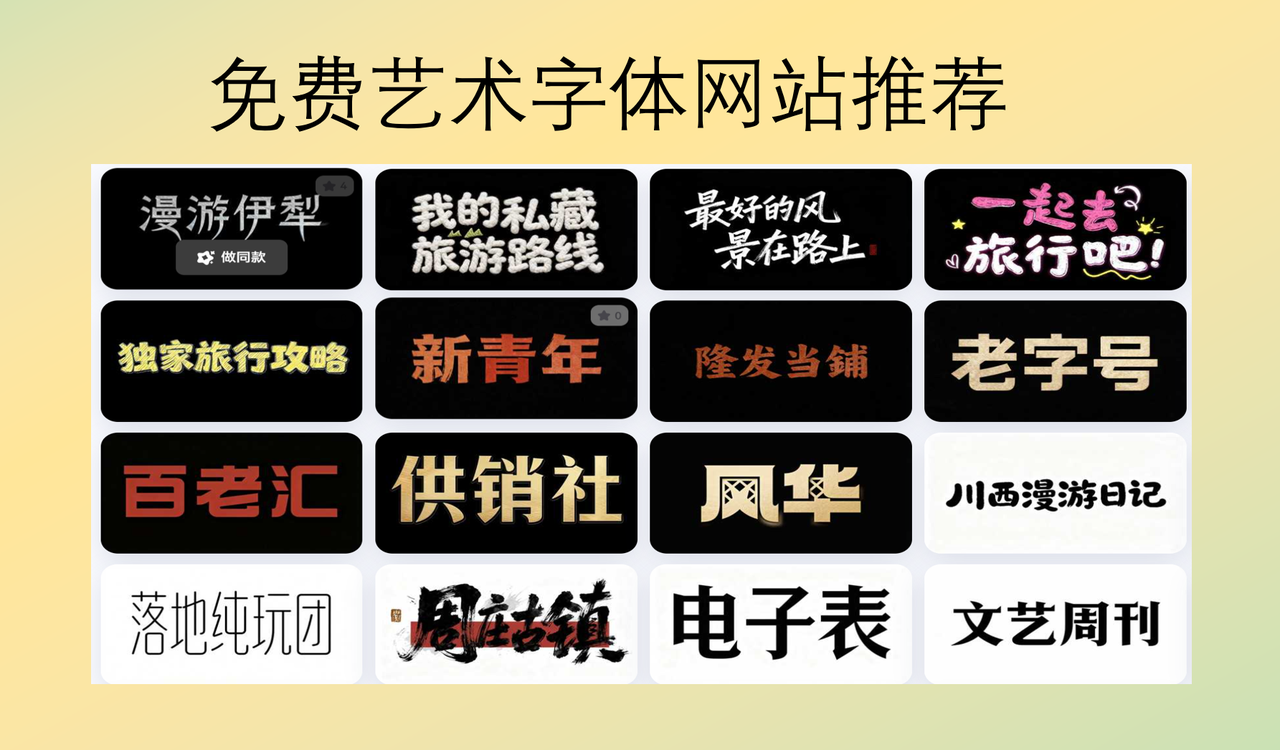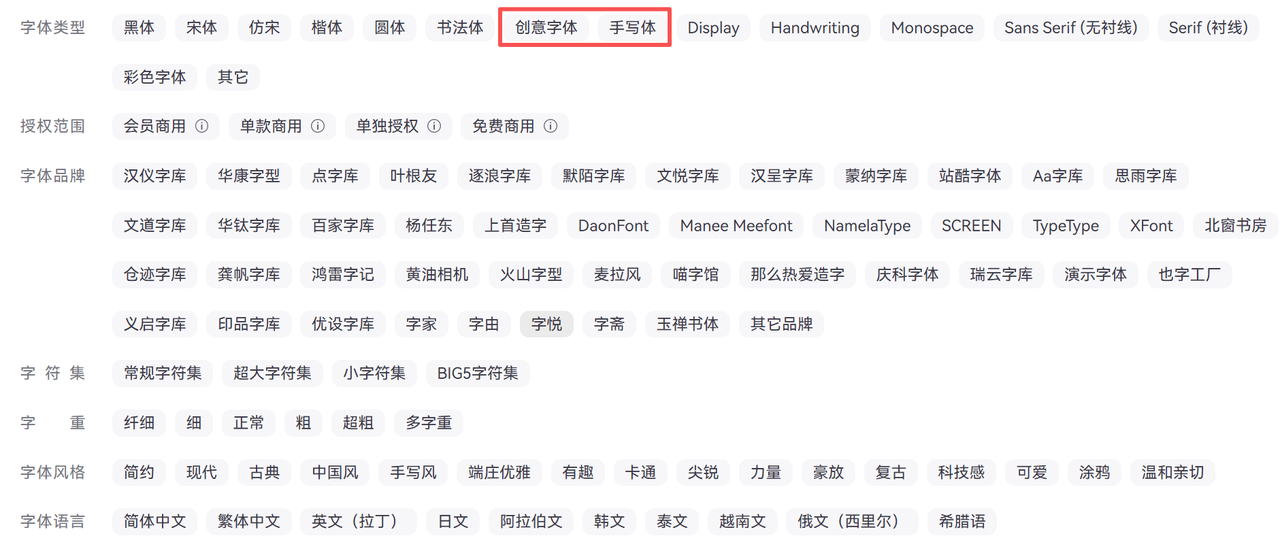
免费艺术字体网站推荐:8个可商用字体平台分享
系统自带的宋体、黑体太普通,想要的艺术字体要么收费,要么下载后发现商用有风险。
我整理了一批真正免费、可商用的艺术字体网站。这些网站不仅字体质量高,而且版权清晰,用上它们之后,我做图效率提升了一半,再也不用担心版权问题。下面分享8个免费艺术字体网站分享给你。
字由拥有非常多的艺术字体资源,并且你不用一个个的下载和安装字体,使用字由客户端就能够快速的激活、使用和管理字体。
筛选分类获取艺术字体
字由通过非常清晰的字体分类,如果想要获取艺术字体,你可以筛选字体类似为“创意字体”、“手写体”,也可以在字体风格中选择“手写风”、“中国风”等艺术分类。
字由除了提供丰富的艺术字体之外,字由 AI 字体还能一键生成艺术字体
打开 AI 生成字体功能页面,根据自己的需求搜索艺术字体类型,比如搜索“霓虹”
进一步筛选自己想要的艺术字体模板,替换为自己的文字,就能一键生成同款艺术字体了。
100font.com
我经常在这里找一些小众但很有个性的字体。上次做咖啡店菜单,用的是"悠哉字体",手写感很强,客户说比之前那版有温度多了。
网站的好处是分类清晰,有"黑体""宋体""手写体""像素体"等标签,还能按字重筛选。每个字体都附上了授权说明文件,下载前能看清楚使用范围。
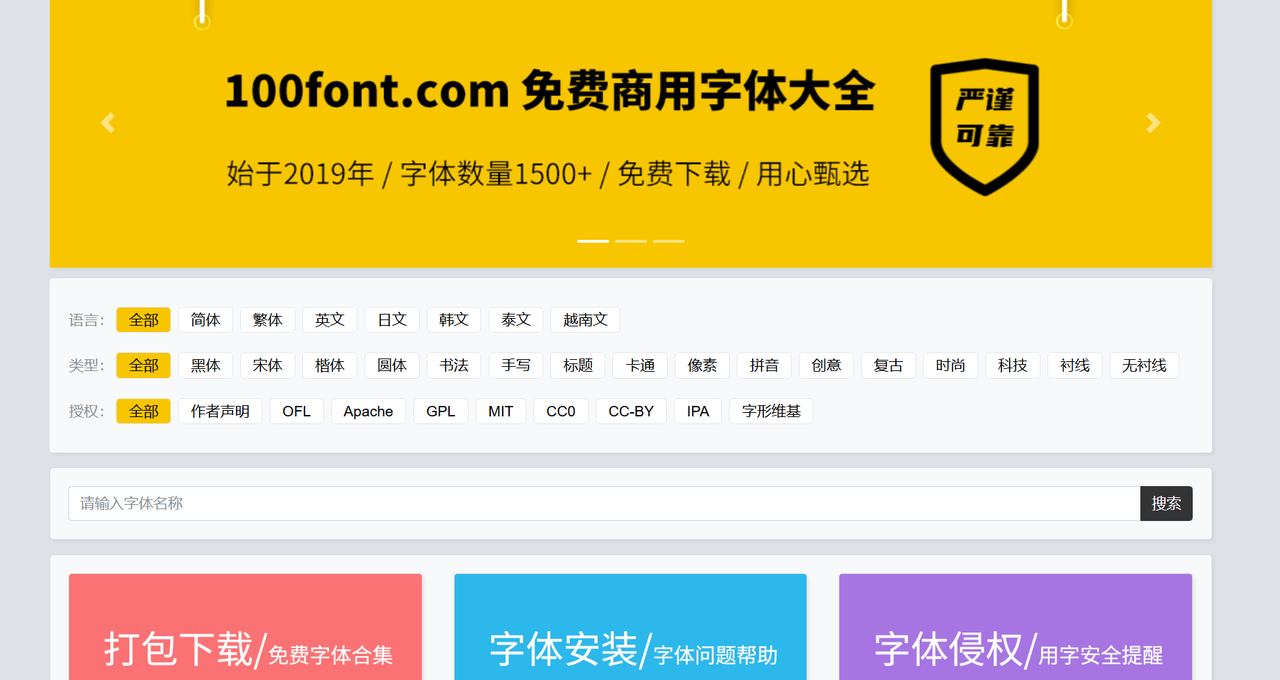
猫啃网
猫啃网是字体爱好者维护的网站,更新很勤快。它最大的特点是会把字体的授权协议翻译成大白话。比如有些字体"个人免费,商用需授权",它会明确写出来,不用你自己去研究繁琐的授权文档。
我在这里发现了"小赖字体"和"沐瑶软笔手写体",都是个人设计师免费开放的,用在手账排版和文艺类海报上效果特别好。
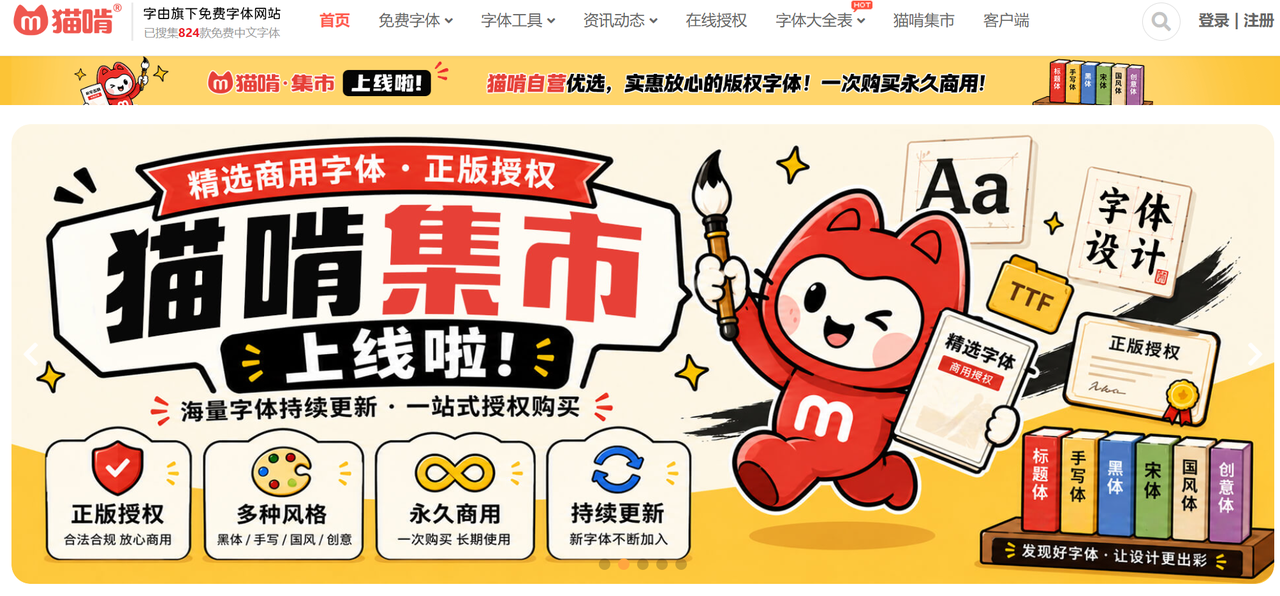
字体天下
老牌字体下载站,资源非常全。虽然里面有付费字体,但免费区的字体也不少。我一般会在搜索时加上"免费"关键词,然后仔细看下载页面的授权说明。
这个网站适合用来找特定风格的字体,比如"广告""海报"等主题字体,它的标签做得比较细。
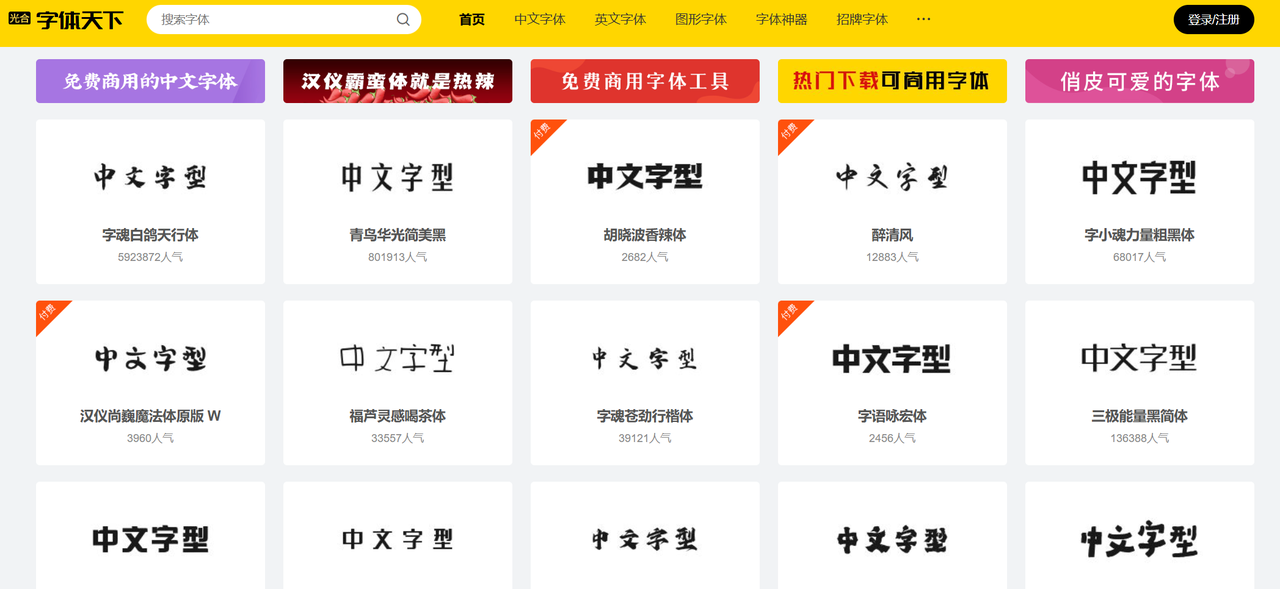
求字体网
这是一个识别字体的网站,但也提供字体下载。我用它最多的场景是:看到别人的设计作品,不知道用的什么字体,就截图上传到求字体网,它会识别出来并提供类似字体的下载链接。
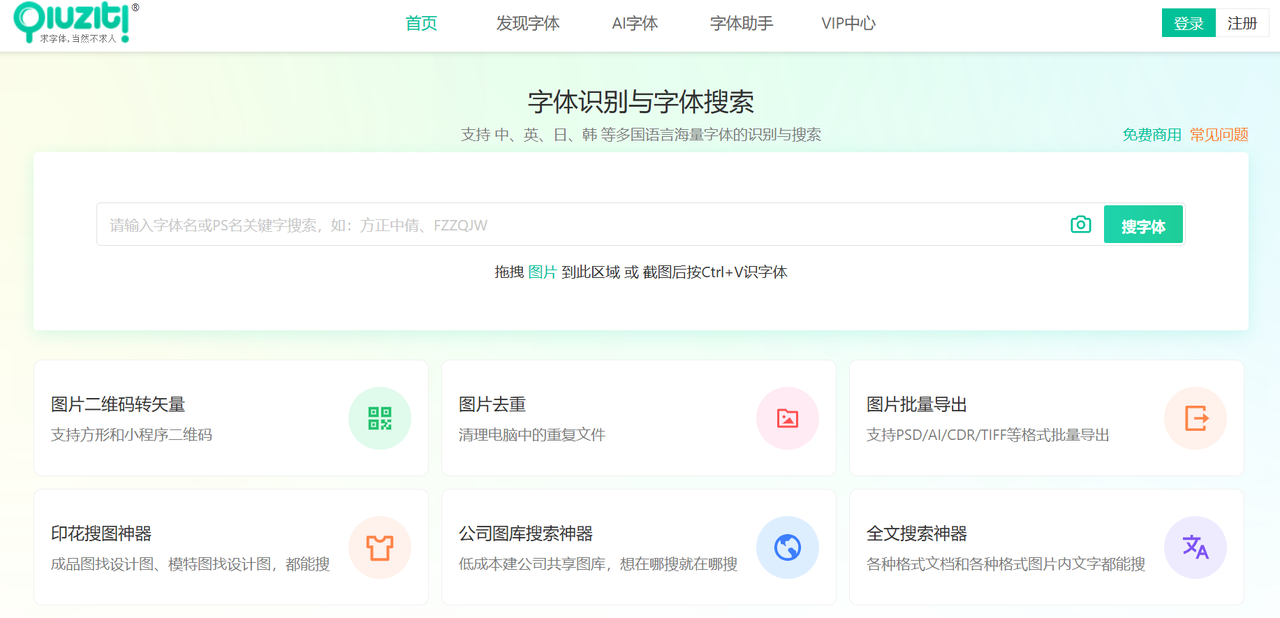
站酷字库
站酷是设计师聚集的平台,他们推出了好几款免费商用字体。"站酷高端黑""站酷快乐体""站酷文艺体"都是我常用的。高端黑适合做科技类海报,快乐体适合活动宣传,文艺体适合书籍封面。这些字体的好处是设计感强,但又不会太夸张,日常工作场景都能hold住。
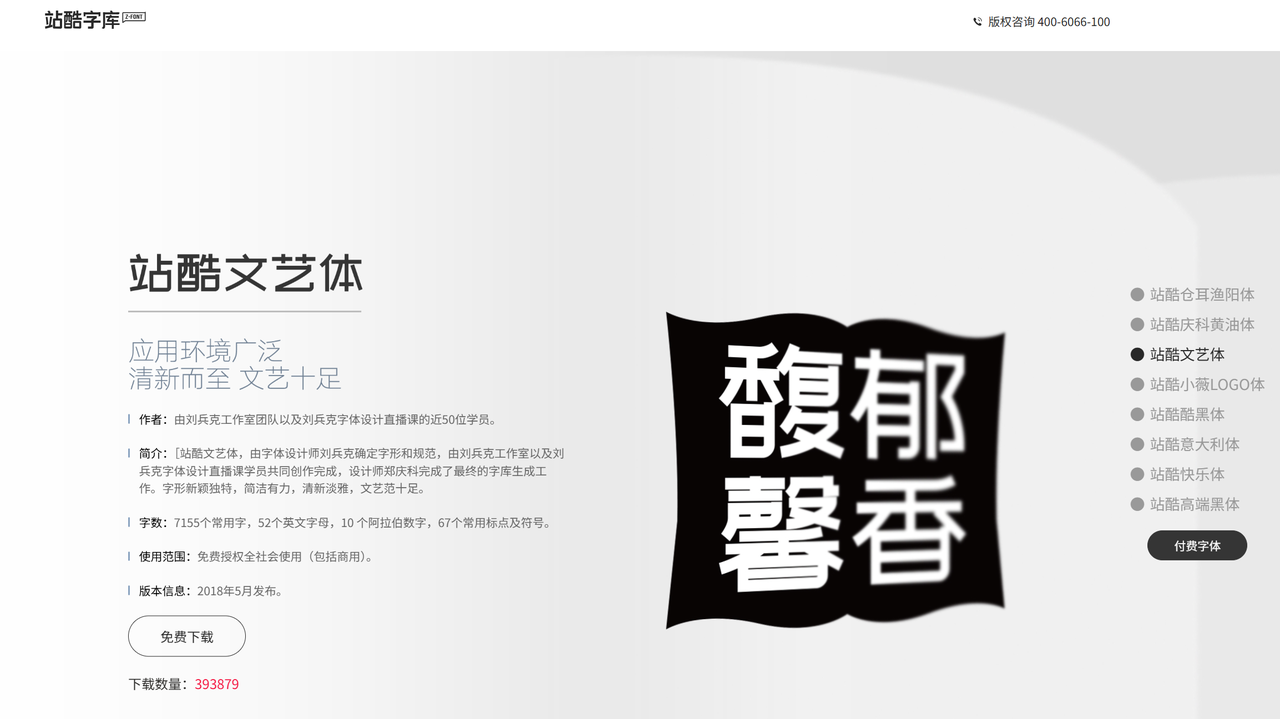
fontsquirrel
英文字体资源库,全部免费商用。我做英文LOGO或者海报标题时会来这里找字体。它有个"Font Identifier"功能,可以通过上传图片识别英文字体,准确率挺高。
推荐它家的手写体和复古字体,比如"Pacifico"和"Bebas Neue",我用在咖啡店和服装店的宣传物料上,客户反馈都不错。
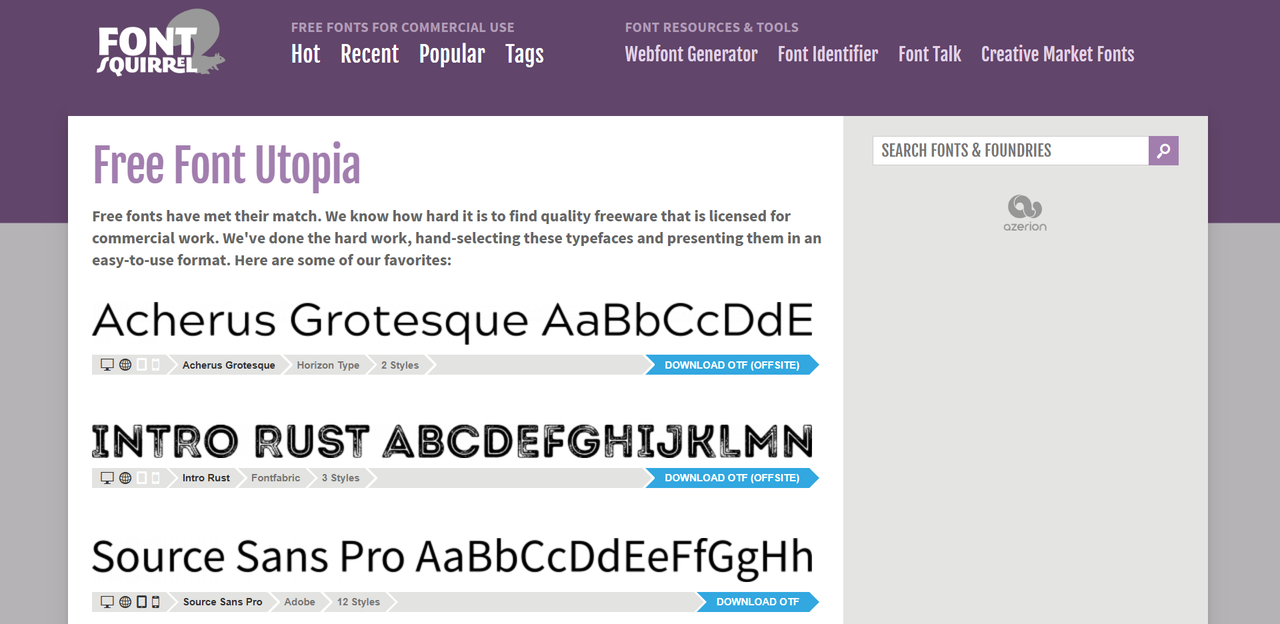
自由字体
这是一个字体导航站,把各种免费字体网站都整合在一起。我一般在找不到合适字体时,会打开这个网站搜索。同时它按风格分类,有"艺术""手写""促销"等分类,省去了一个个网站翻的时间,适合赶急活的时候用。
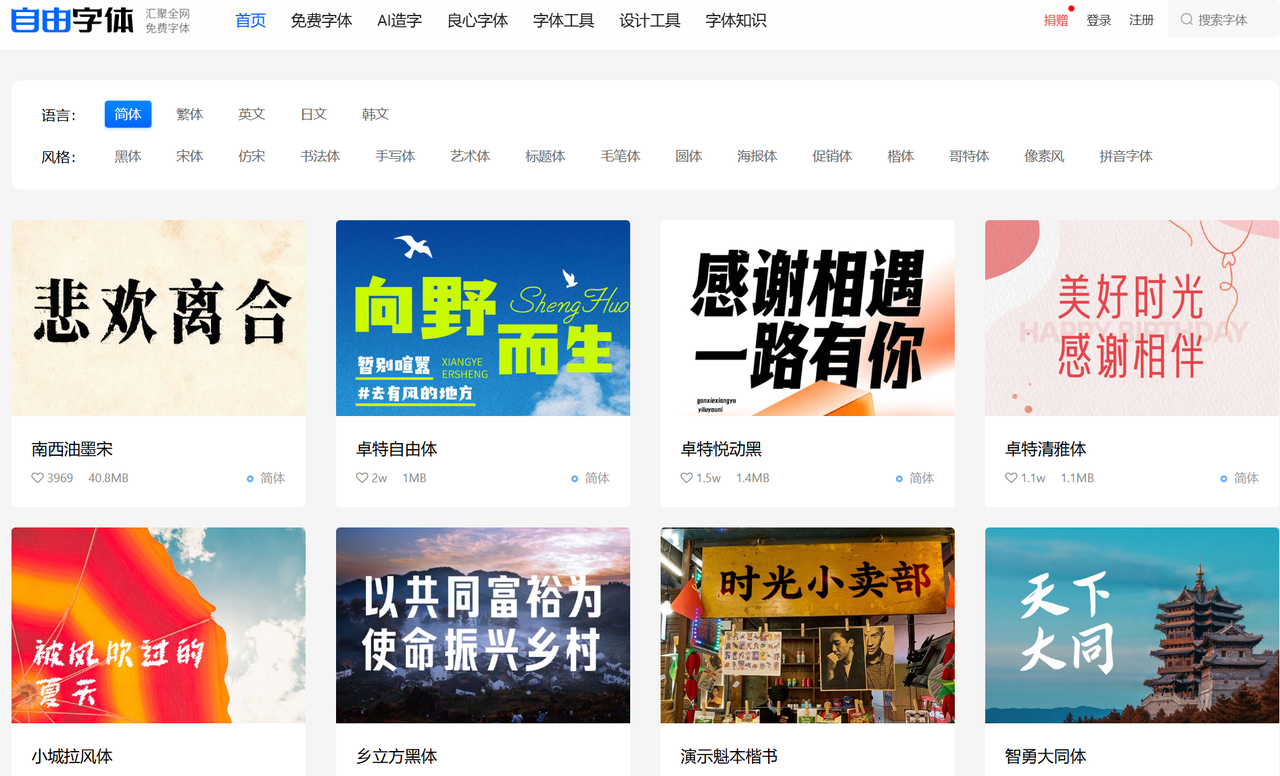
我的使用建议
用了这么久免费艺术字体网站,我总结几个经验:
多看优秀案例。字体不是越花哨越好,要和设计内容匹配。字由同样也给大家提供非常丰富的字体案例,帮你提供字体设计思路。